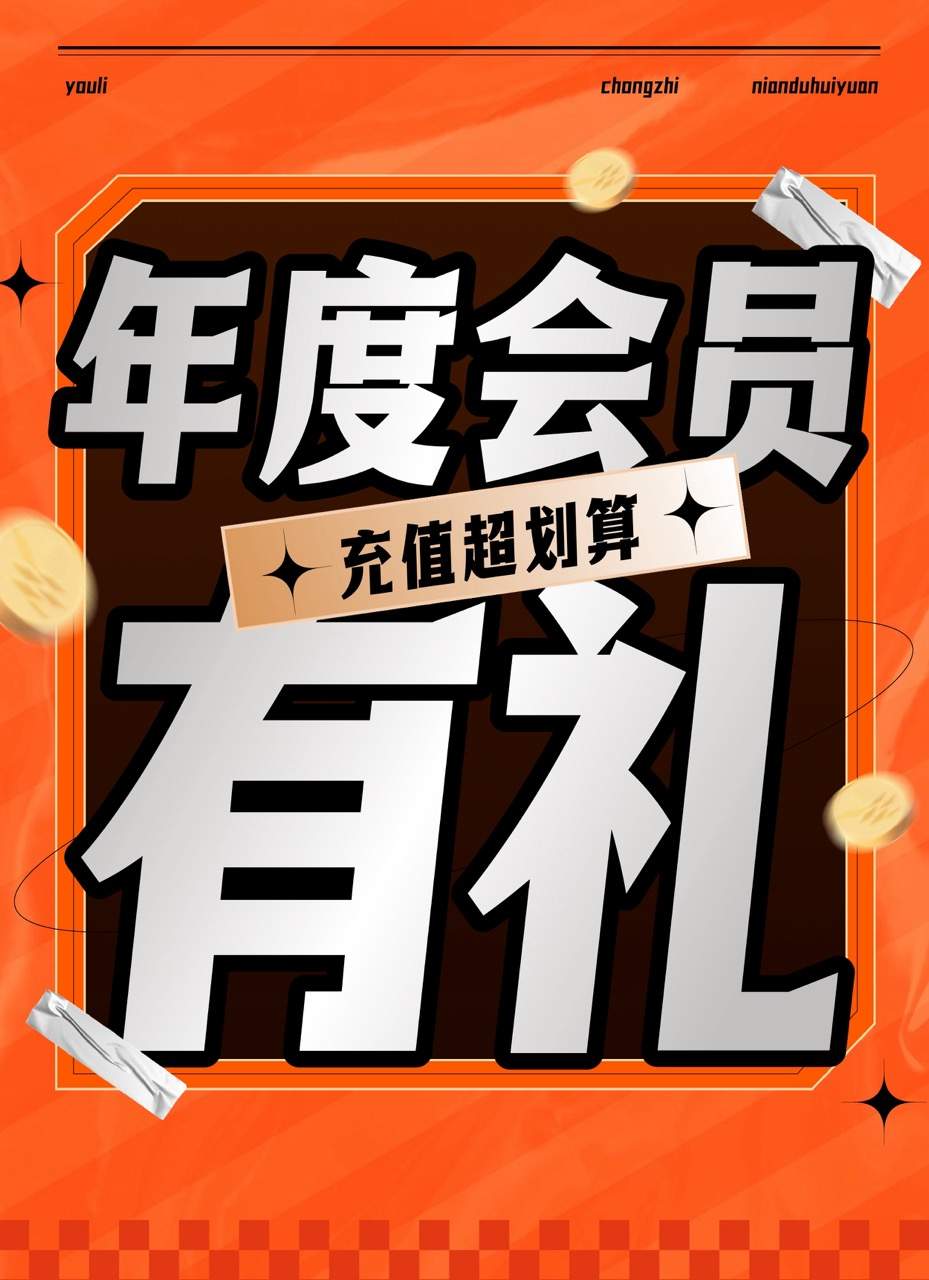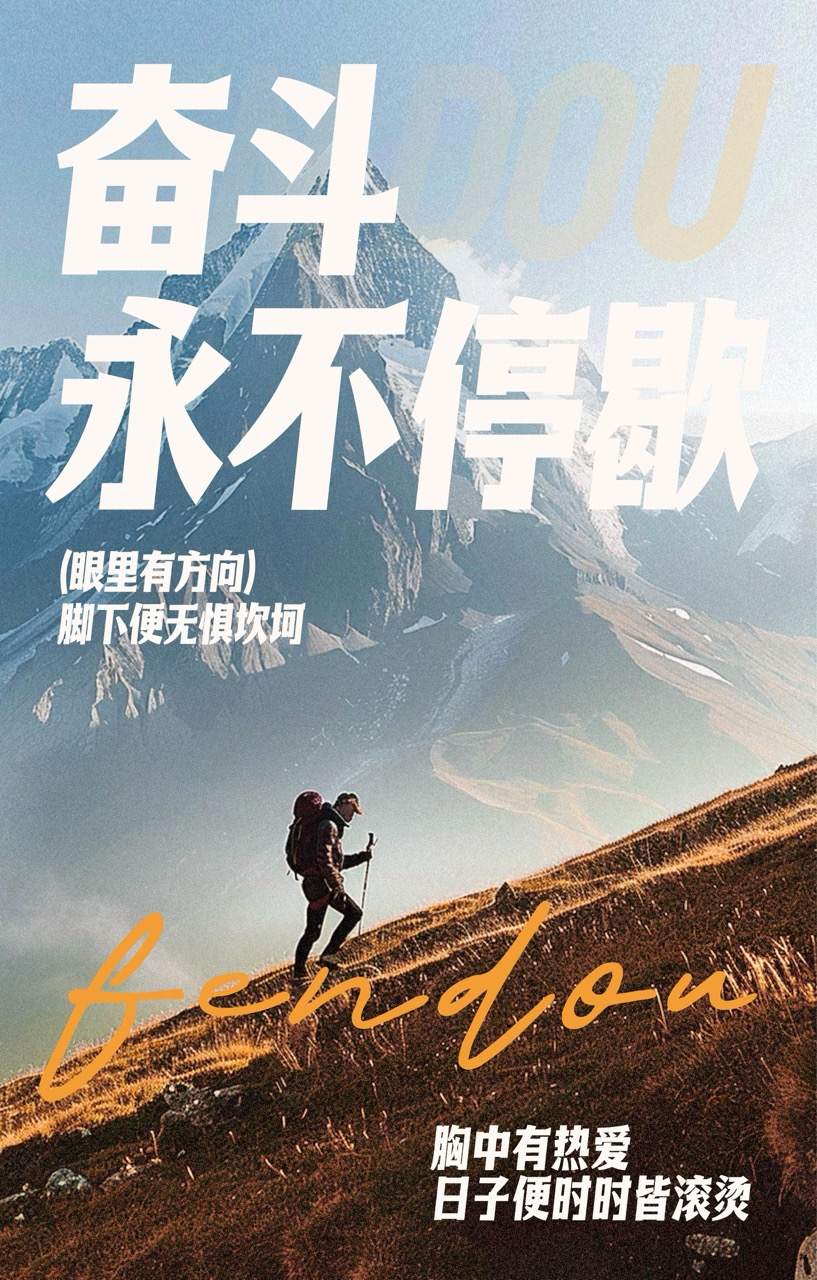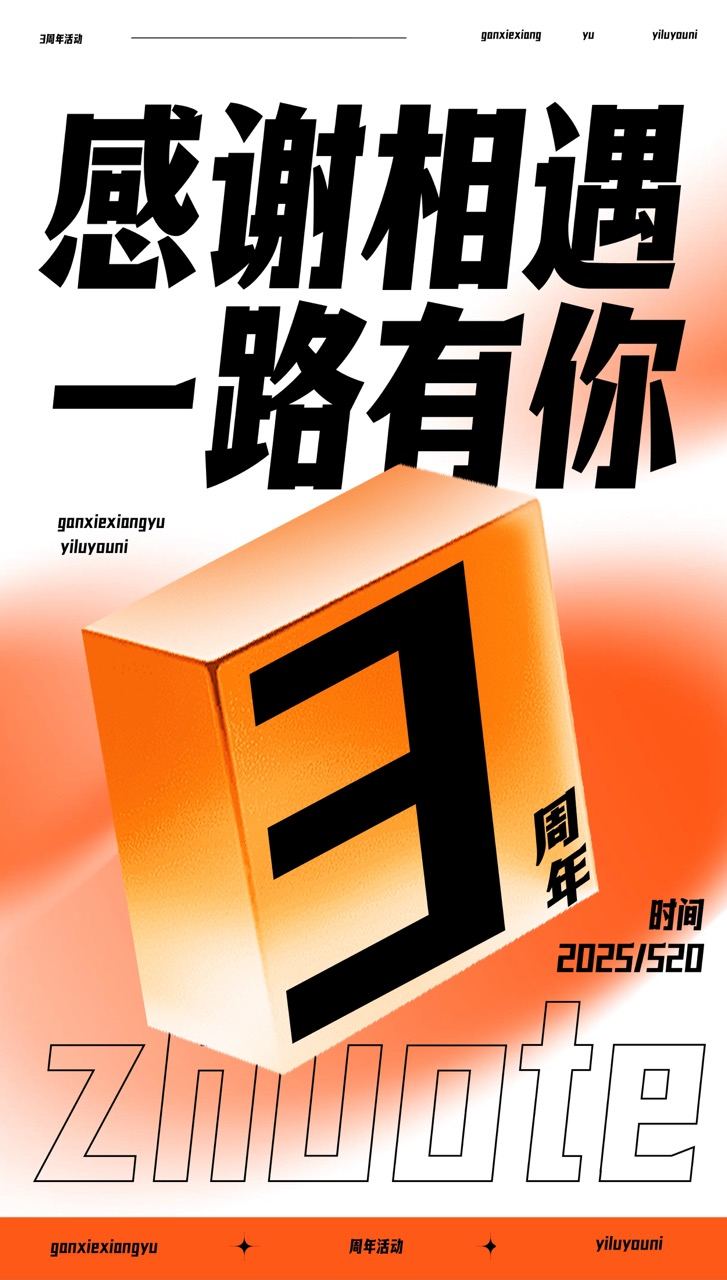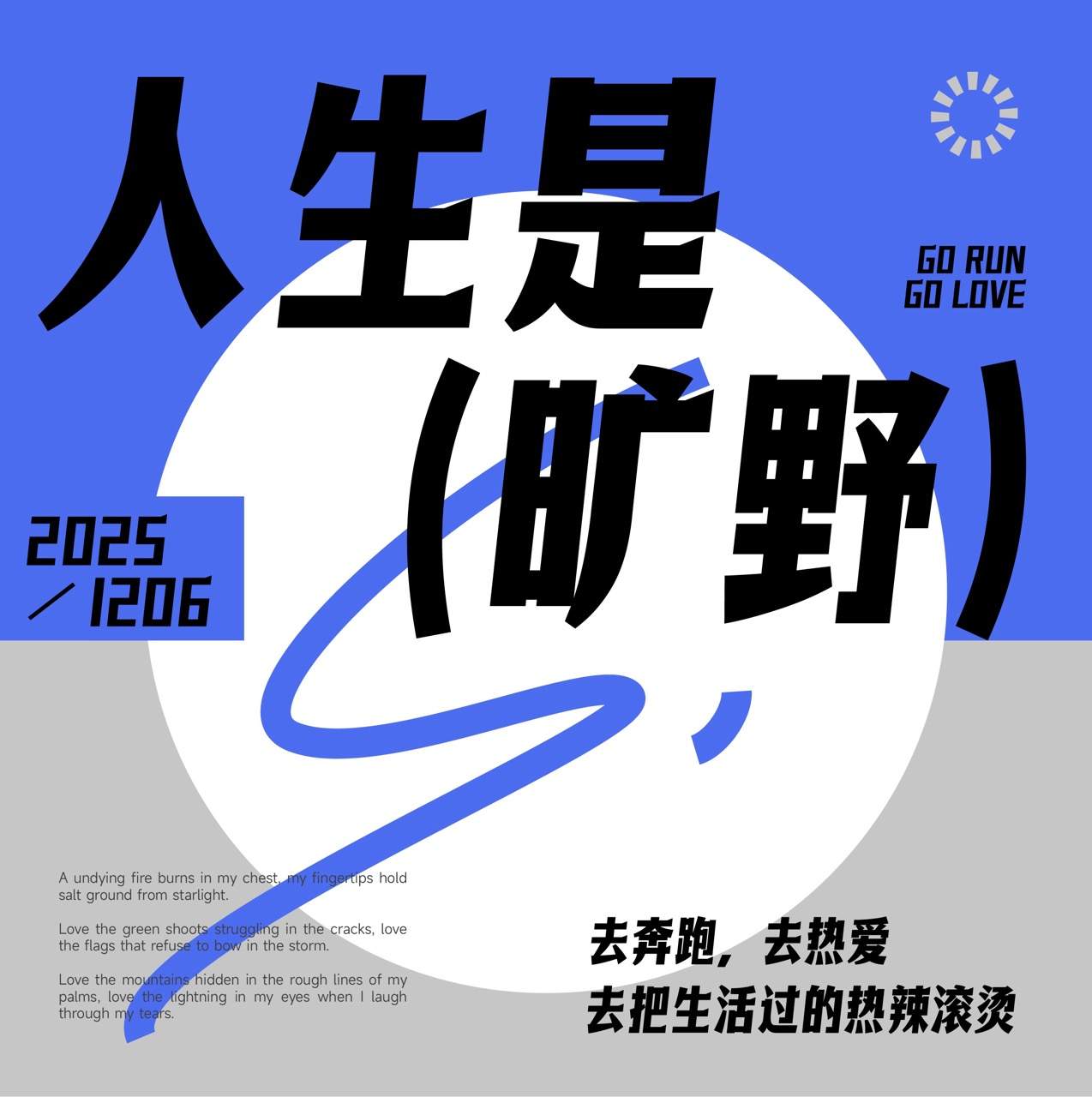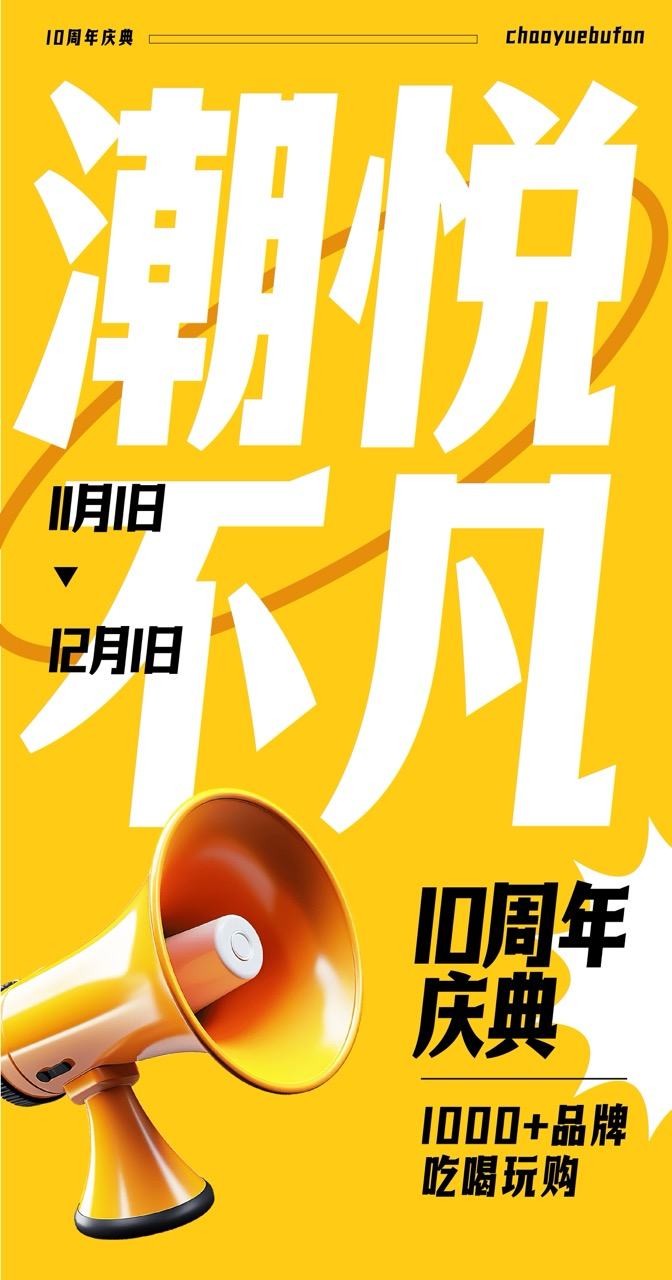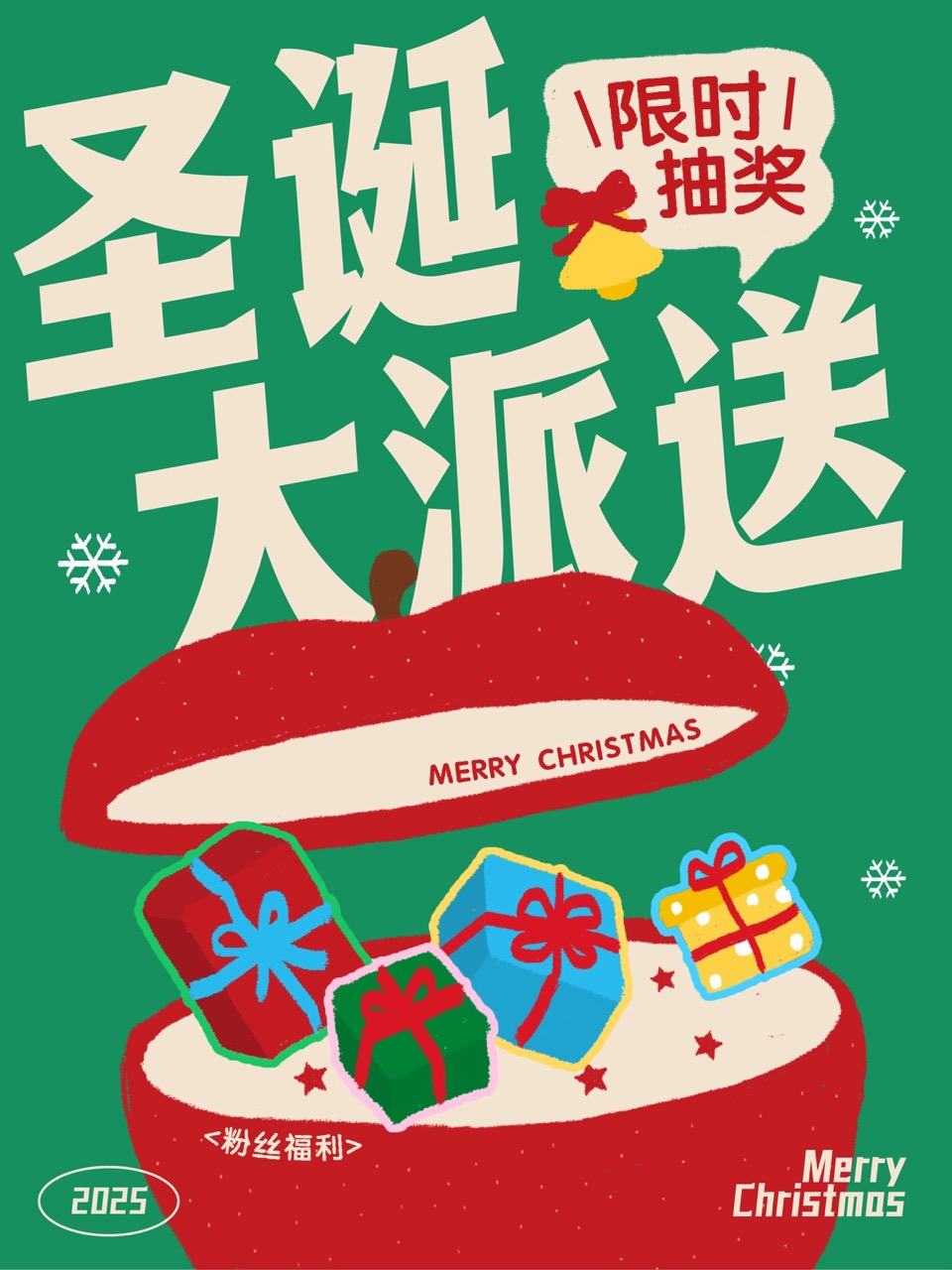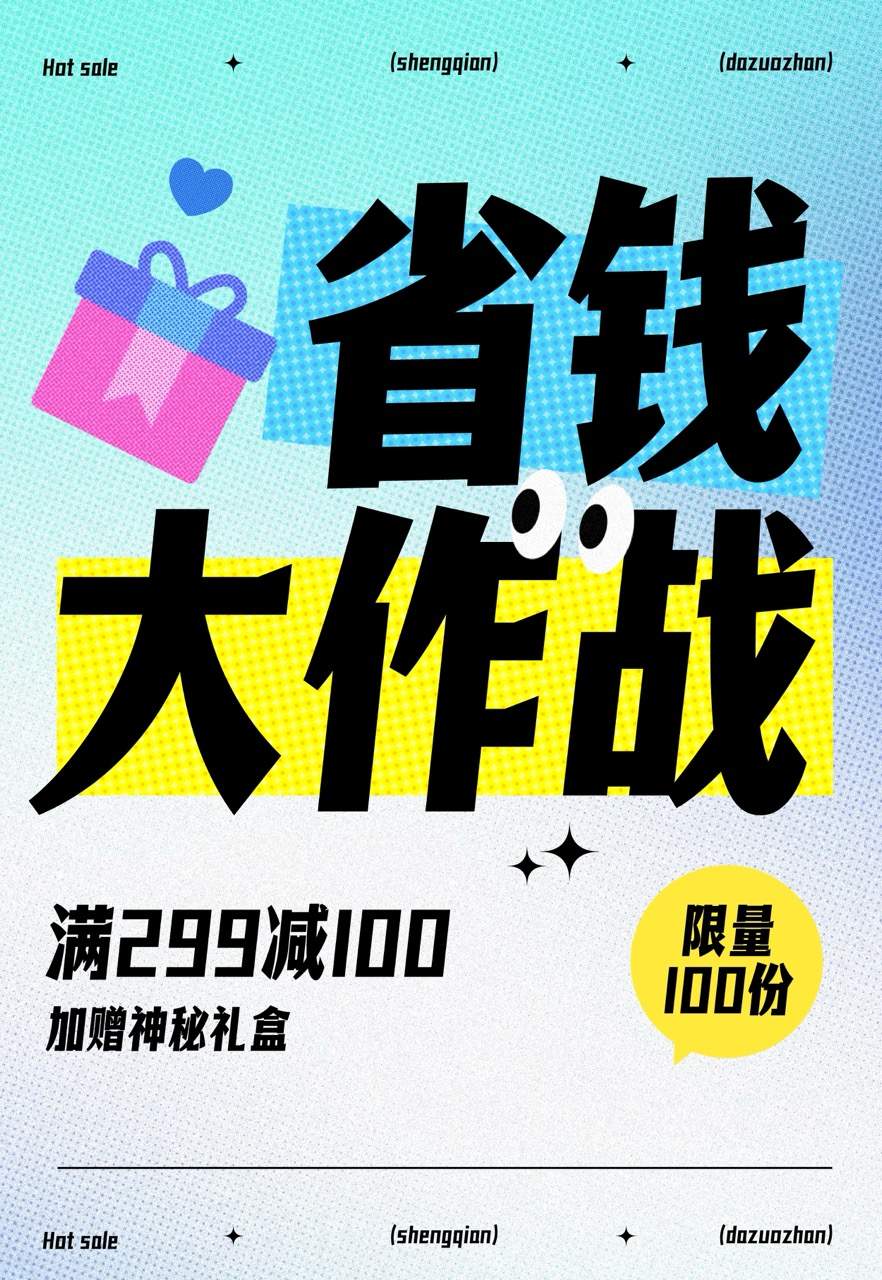
卓特悦动黑 力量速度 张力十足
字形高挑饱满,笔画厚实有力,富有强烈的力度感和动势。结合近代印刷美术字特征,横画外侧带有独特的尖角装饰。
• 字形高挑饱满,笔画厚实
• 富有力度感和动势
• 横画外侧尖角装饰
卓特悦动黑 ZTYueDongHei 开源免费可商用高挑动势尖角粗黑体 刘兵克×卓特视觉出品